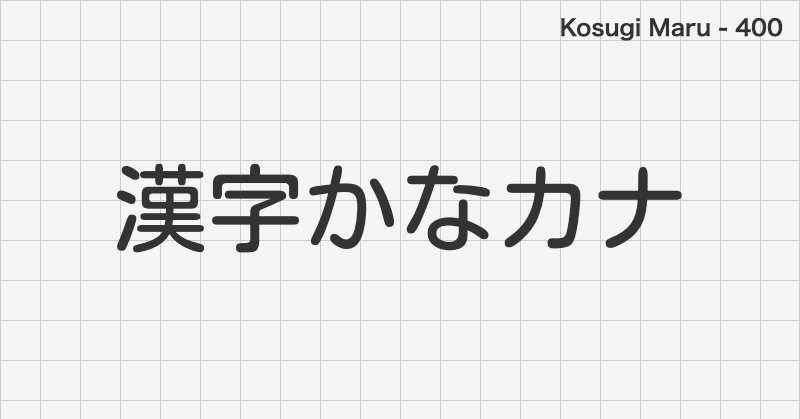
Kosugi Maru は、低いストロークコントラストとモノスペースのメトリクスを持つゴシック体フォントで、丸みを帯びた端が特徴です。美しさと可読性を追求したデザインです。
日本語ラテン文字ラテン文字拡張キリル文字 に対応しており、多言語環境でも統一したデザインで表示できます。
Kosugi Maru は、MOTOYA によって開発され、1950年代のデザインに基づいています。特に、日本の杉の木をイメージしたデザインが印象的です。